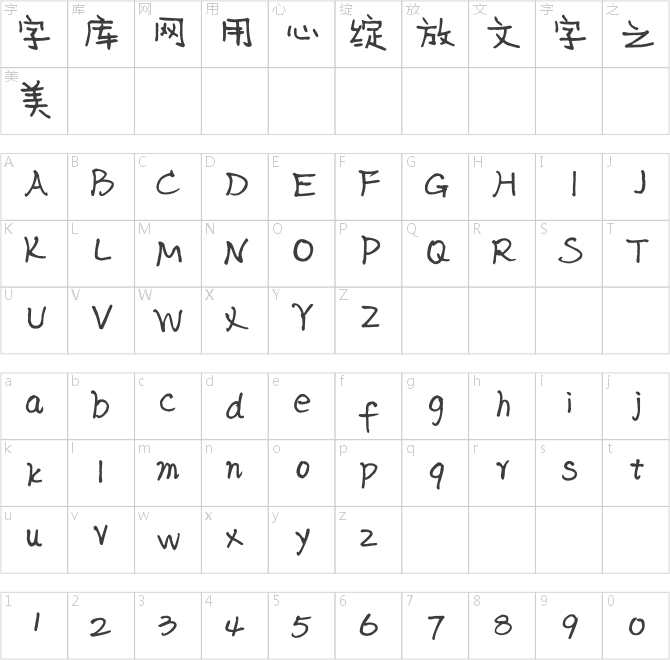
陳繼世神韻曉雯體 詳情頁
神韻曉雯體字體是一款由神韻字庫設(shè)計(jì)師陳繼世打造的藝術(shù)字體,該字體將筆畫夸張,筆畫與筆畫采用非常規(guī)處理,結(jié)構(gòu)歪斜,重心不穩(wěn),使人產(chǎn)生青澀、萌動(dòng)的感覺,能夠適用于藝術(shù)設(shè)計(jì)、包裝印刷、簽名設(shè)計(jì)、圖形設(shè)計(jì)等應(yīng)用。(本字體為個(gè)人非商用版,如需要商用請(qǐng)聯(lián)系作者購買版權(quán))
陳繼世神韻曉雯體字體字庫是一款讓人賞心悅目、百看不厭的中文字體,適合各類廣告和產(chǎn)品包裝設(shè)計(jì)應(yīng)用,字體大小2.33MB,格式為ttf字體,上傳用戶是神韻,作者/版權(quán)方為神韻字庫